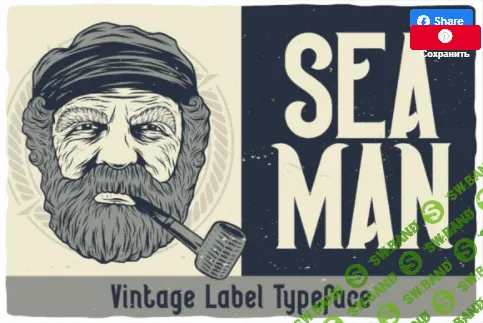
Название: Seaman Font (2021)
[creativefabrica] Seaman Font (2021)
Seaman - это крутой, жирный шрифт в винтажном стиле. Независимо от темы, этот шрифт будет невероятно полезен для вашей библиотеки шрифтов, поскольку он может улучшить любое творение.